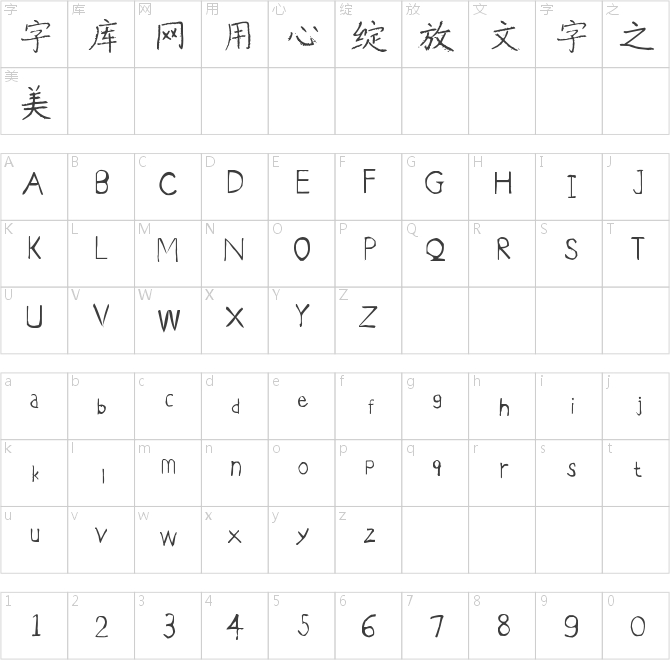
字體名稱: 漢呈想大聲告訴
漢呈想大聲告訴你
漢呈想大聲告訴你字體字庫(kù)是一款讓人賞心悅目、百看不厭的中文字體,適合各類廣告和產(chǎn)品包裝設(shè)計(jì)應(yīng)用,字體大小5.33MB,格式為ttf字體,上傳用戶是小猴子1003,作者/版權(quán)方為漢呈字庫(kù)